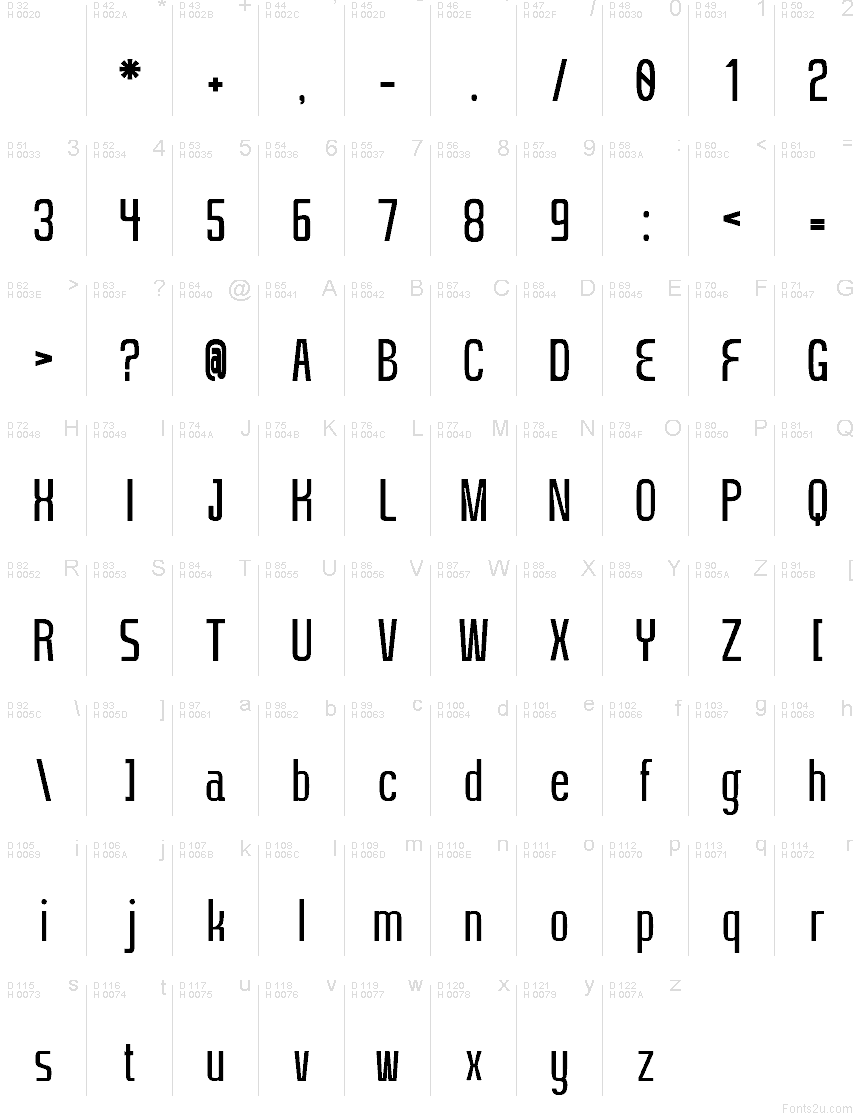
Cranity, dzieło Afkari Studio, to bezpłatny krój bezszeryfowy o zaokrąglonych kształtach, utrzymany w miękkim, współczesnym stylu. Litery wydają się wysokie i oszczędne w formie, z łagodnymi narożnikami, równymi kreskami i prostą geometrią, która nadaje całości spokojny, a nie surowy wyraz.
Dzięki temu ten darmowy font jest naturalnym wyborem dla brandingu aplikacji, logotypów startupów, etykiet produktów, nagłówków plakatów czy grafik w mediach społecznościowych, wszędzie tam, gdzie poszukujesz nowoczesności pozbawionej ostrych krawędzi. Sprawdzi się również w krótkich tytułach i subtelnych podtytułach redakcyjnych, ponieważ hojne krzywe i przewiewne światła między znakami nadają słowom lekki, otwarty rytm.